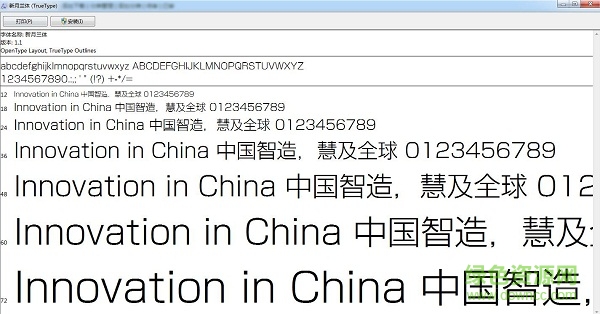
新月蘭體 粗體/亮體
新月蘭字體是一款日本無襯線字體,包含了粗體和亮體兩款,內(nèi)部空間大小適中,比例合當(dāng),適用于屏幕顯示、平面設(shè)計(jì)等各個(gè)領(lǐng)域,有需要著歡迎免費(fèi)下載!
新月蘭體特點(diǎn)
一款筆畫較細(xì)的日系舊字形字體,新月蘭是以日文Shingo的舊字形漢字,以蘭亭纖黑補(bǔ)全的一個(gè)合并字體。英文數(shù)字可以搭配Lato Light使用。
新月蘭體 粗體